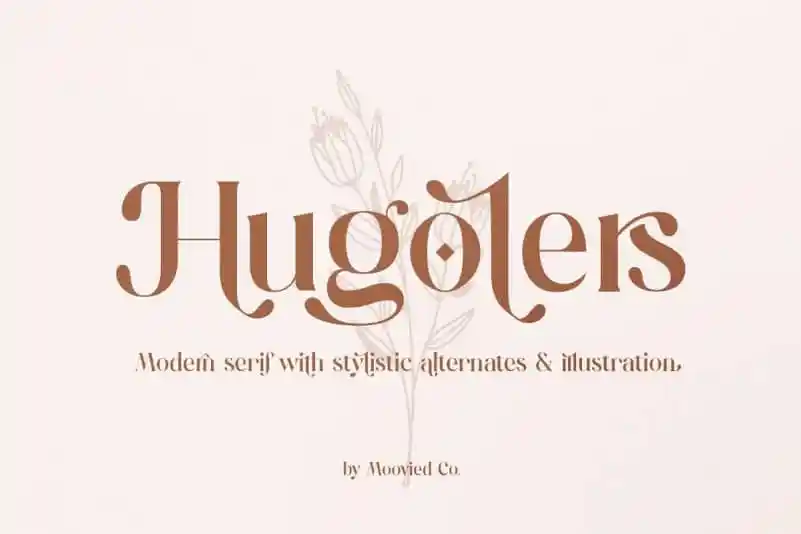
Hugolers Stylish Serif Font – Download Grátis
A Hugolers Stylish Serif Font é uma escolha perfeita para quem busca uma mistura sofisticada e moderna do mundo dos tipos serifados. Com 100+ alternativas, esta fonte oferece a beleza única e versátil de um tipo serifado vintage em uma tipografia contemporânea. Seu design equilibrado e atual permite que você combine essas alternativas para criar formas elegantes e curvas fluidas, tudo isso na velocidade do pensamento. Esta fonte foi criada por Moovied Co., uma empresa de design atenta às últimas tendências gráficas e capaz de oferecer alternativas e ligaturas que permitem a criação de logotipos impressionantes, publicações inspiradoras, invitações para casamentos, imagens para revistas e muito mais. Perfecto para quem busca um toque sofisticado em suas composições, sem perder a personalidade vintage que torna os serifados únicos e memoráveis.